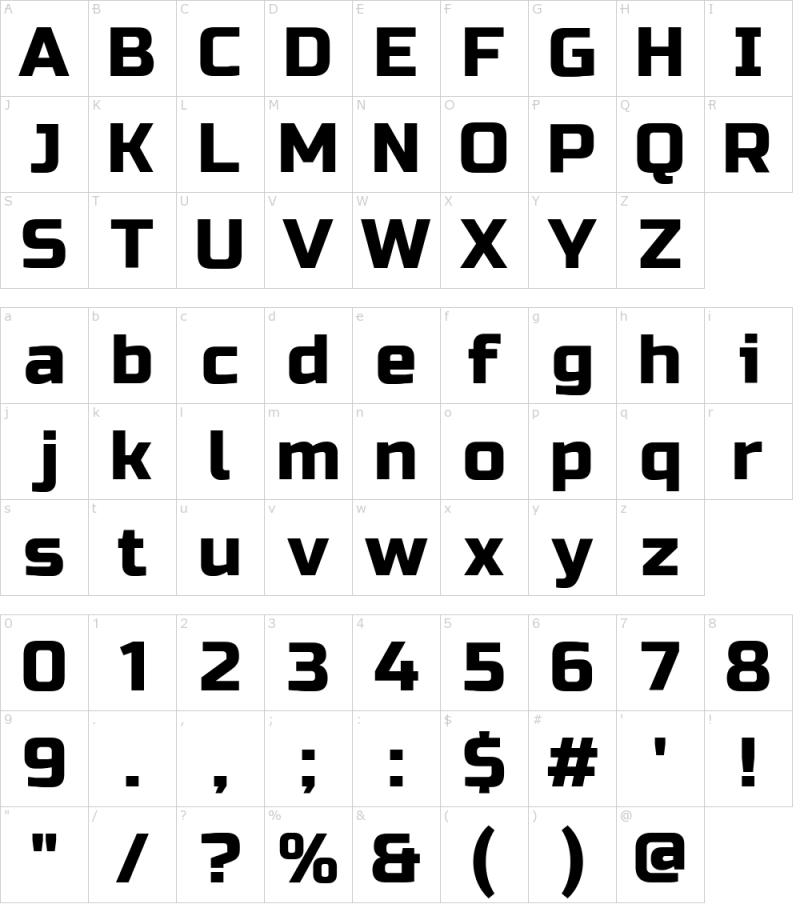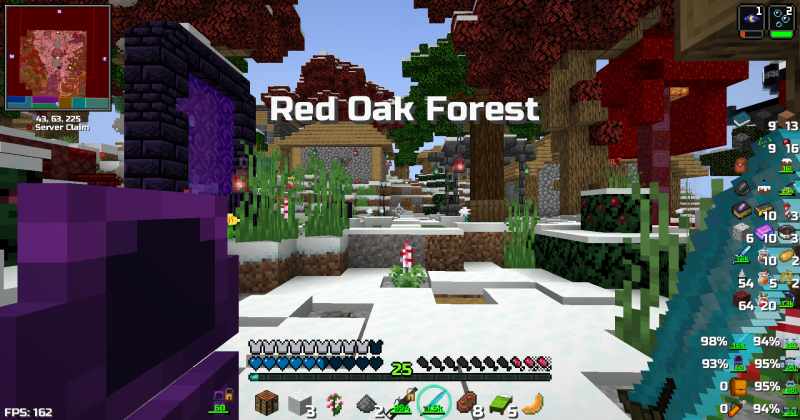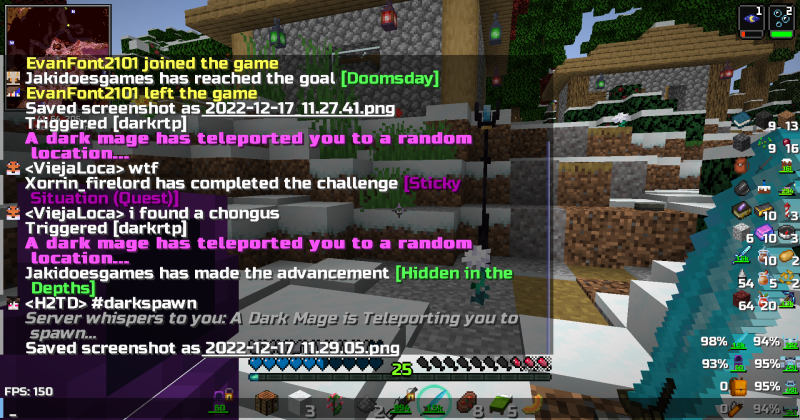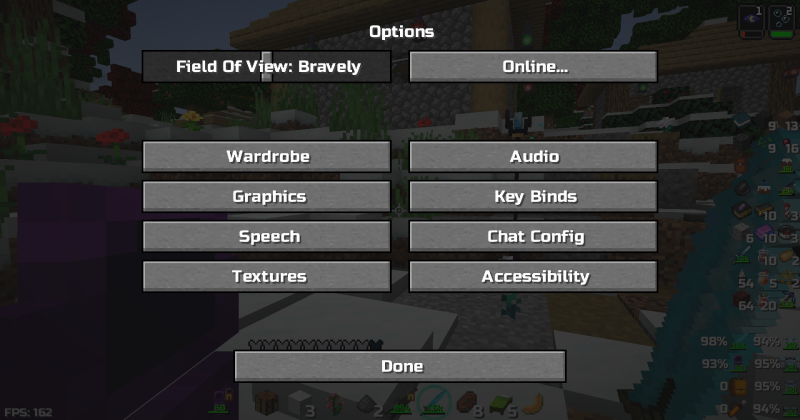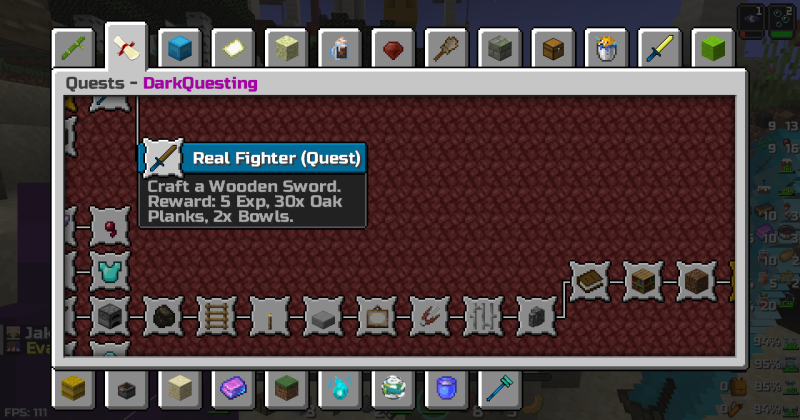
Super RPG Font 26.3/1.21.11 (Современный шрифт для RPG 32x)
Super RPG Font предлагает свежий взгляд на текстовое оформление в Minecraft, заменяя стандартный шрифт на современный гладкий вариант. Новый шрифт отличается чёткостью и лёгкой читаемостью, что делает его отличным выбором для игроков, ценящих удобство и стиль в интерфейсе.
Визуально шрифт выполнен в плавном современном стиле, который хорошо сочетается с различными тематиками, особенно с RPG-атмосферой. Он не перегружает экран, сохраняя баланс между эстетикой и функциональностью, что улучшает общее впечатление от игры без изменения игровых механик.
• Гладкий и современный дизайн шрифта
• Улучшенная читаемость текста в интерфейсе
• Стиль, подходящий для RPG-тематики
• Основан на популярном шрифте Russo One